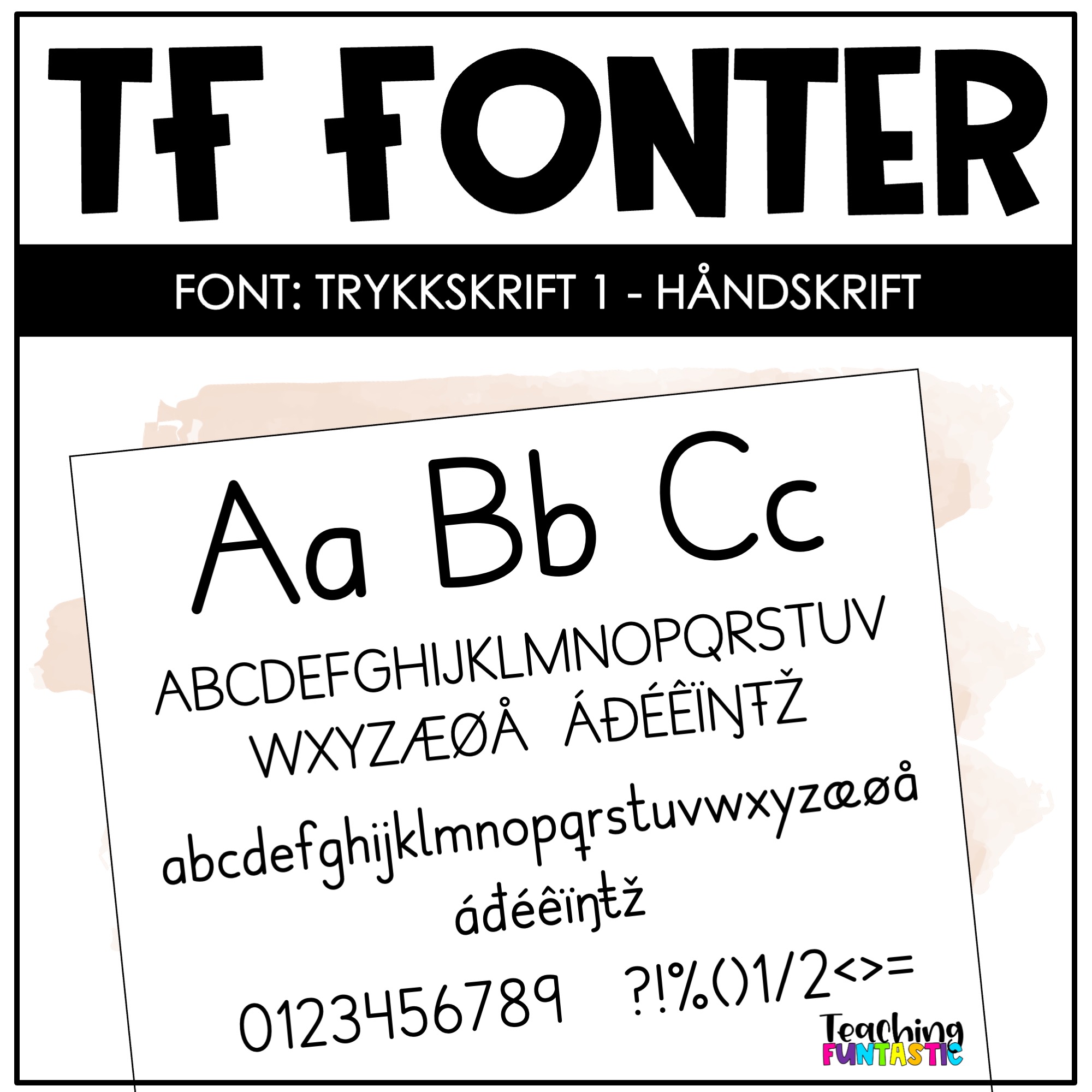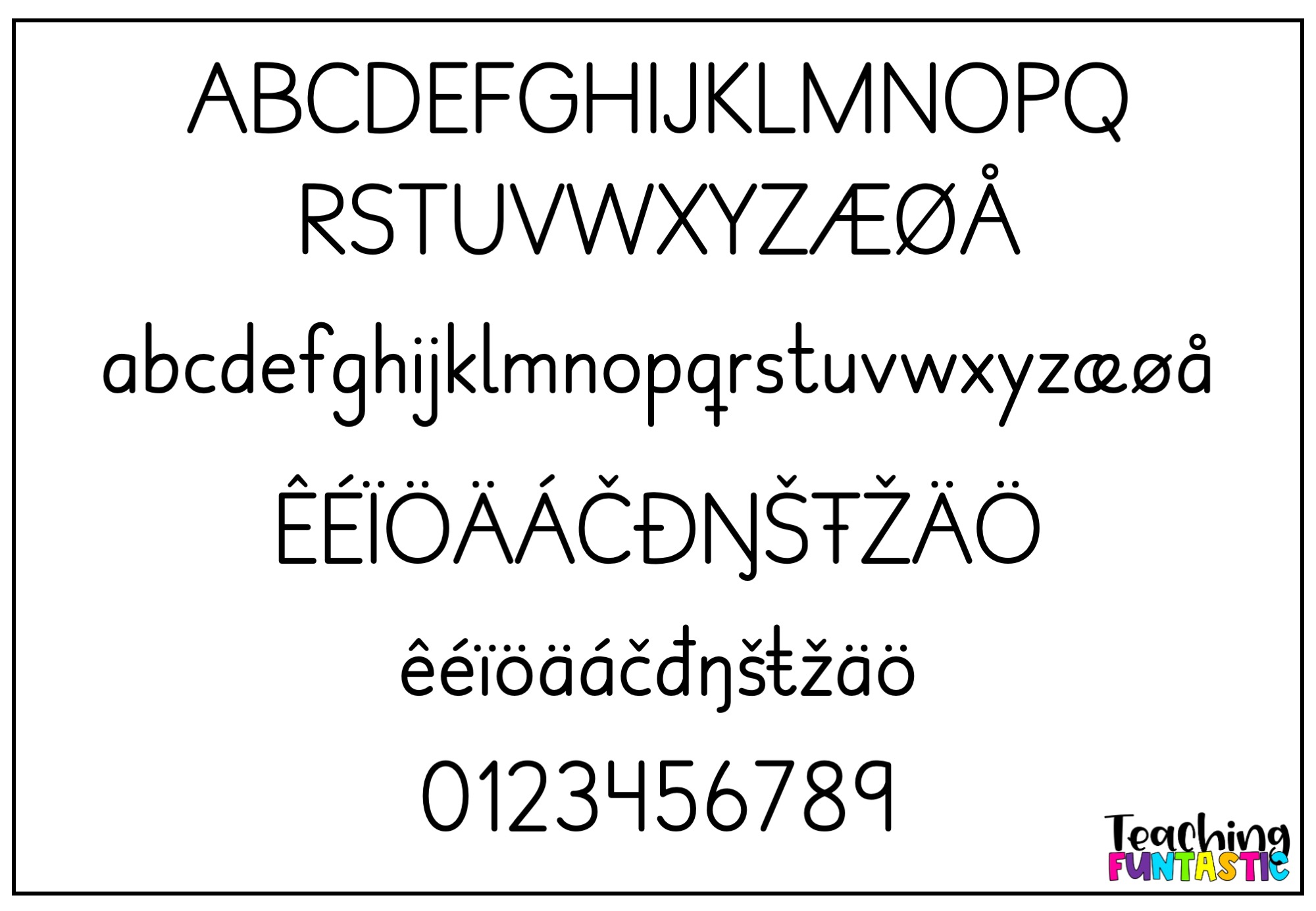
FUNtastic Trykkskrift 1 – håndskrift font for skole og undervisning
FUNtastic Trykkskrift er en enkel og tydelig font håndskrift utviklet spesielt for lærere og elever i begynneropplæringen. Den etterligner den trykkskriften elevene lærer å skrive selv, og passer perfekt i alt fra arbeidsark og lesehefter til plakater og oppgaver. Denne fonten for skolebruk gjør det lettere for elevene å kjenne igjen bokstavformene de jobber med hver dag – og bidrar til trygghet og mestring i lese- og skriveopplæringen.
Fonten Håndskrift – Trykkskrift 1 har bokstaver med rette streker, uten “hale”.
Lesbar håndskrift font for barn
Når barn møter for mange ulike skrifttyper tidlig i leseprosessen, kan det føre til forvirring. FUNtastic Trykkskrift har et rolig og konsekvent uttrykk, og hjelper elevene å fokusere på bokstav-lyd-forbindelser i stedet for å avkode stadig nye bokstavformer. Den jevne linjeføringen og god avstand mellom bokstavene gjør dette til en lesbar font for barn, også for elever med lesevansker. Den støtter naturlig bokstavgjenkjenning og bidrar til bedre flyt i både lesing og skriving.
Skrifttype tilpasset for lærere og skoler
Norsk font med alle bokstaver
FUNtastic Trykkskrift er en font med alle de norske og samiske bokstavene, slik at du slipper kompromisser i norskspråklig undervisningsmateriell. Bokstavene har balansert høyde og avstand for best mulig lesbarhet, både på skjerm og utskrift, slik at den fremstår klar og leselig uansett størrelse.